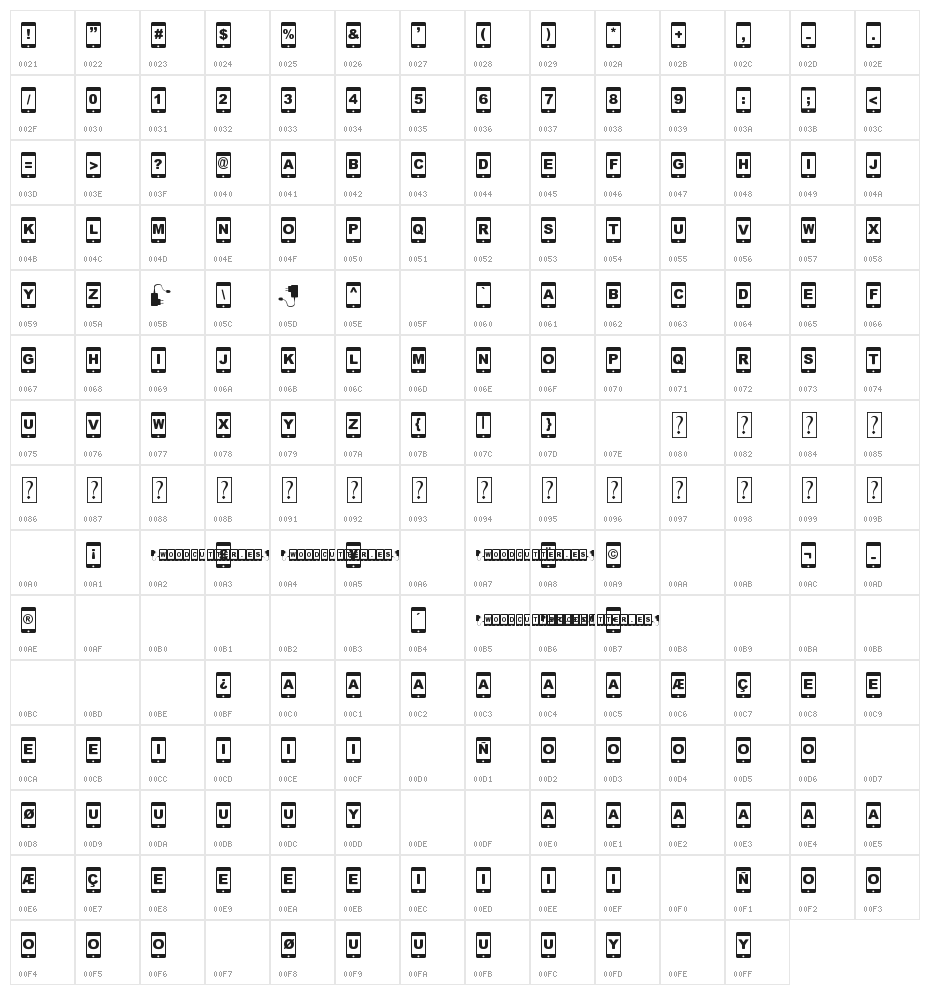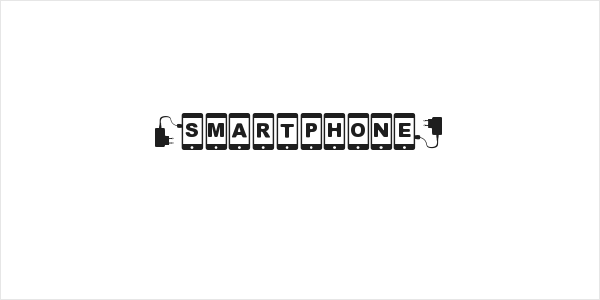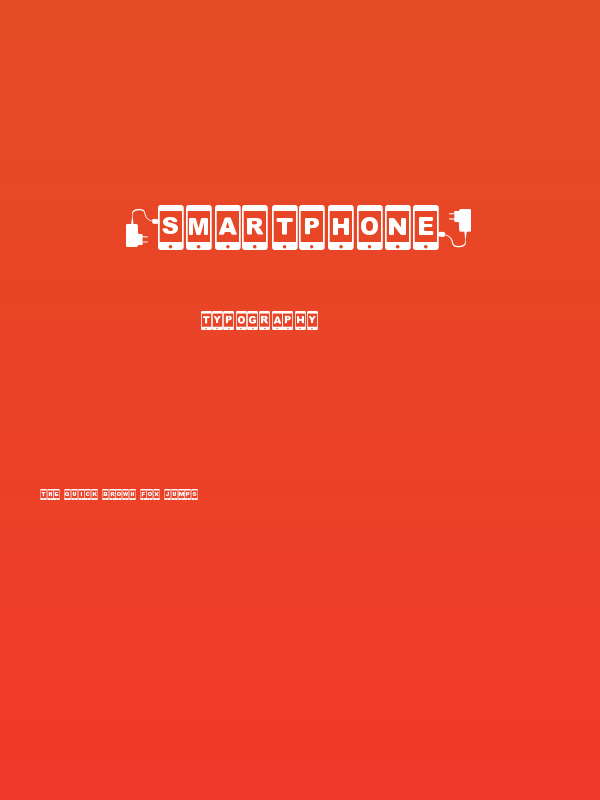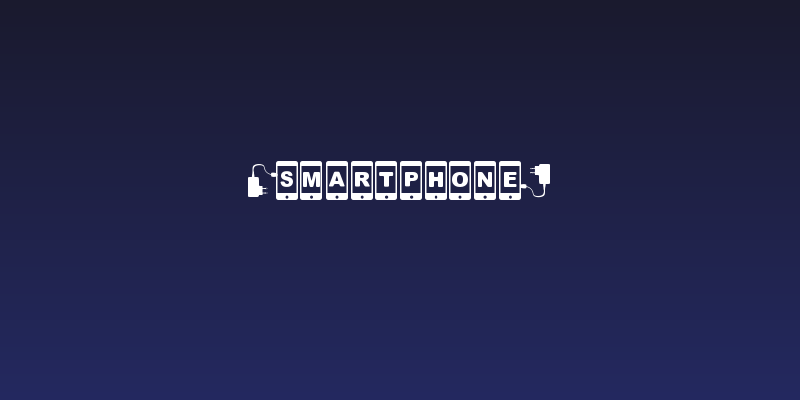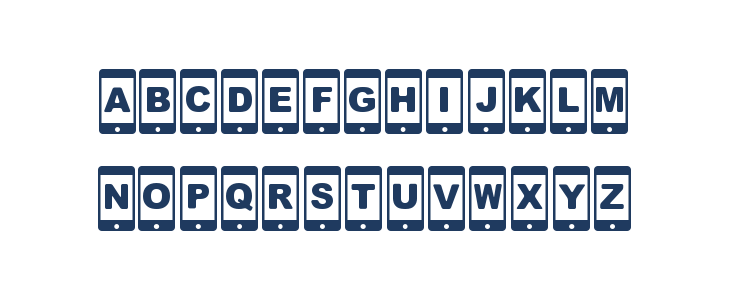
[smartphone] Font
| Caso d'uso | Logos, Headlines, Digital Media |
| Progetti proposti | Ideal for tech-related branding, app design, digital marketing materials, and educational tools focusing on technology. |